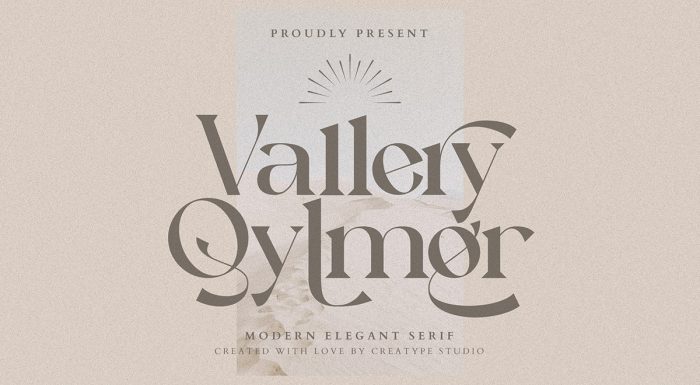
فونت Vallery Qylmor انگلیسی
دانلود فونت Vallery Qylmor انگلیسی Font والری کیولمور رایگان |
| ⭐ توضیحات | والری کیلمور – Vallery Qylmor Modern Business یک فونت سریف مدرن و شیک است. این فونت بسیار ساده و شیک به نظر میرسد. به خصوص طراحی شده توسط دستان ماهر، این فونت برای تمام پروژههای بزرگ شما مناسب است.
فونت والری کیلمور برای پروژههای برندینگ، لوگو، طراحیهای عروسی، ارسالهای رسانههای اجتماعی، تبلیغات، بستهبندی محصول، طراحی محصولات، برچسب، عکاسی، دعوتنامه، لوازم تحریر و هر پروژهای که به طعم نوشتن نیاز دارد، مناسب است. آنچه در بسته دانلود وجود دارد: – تعداد زیادی گلیف |